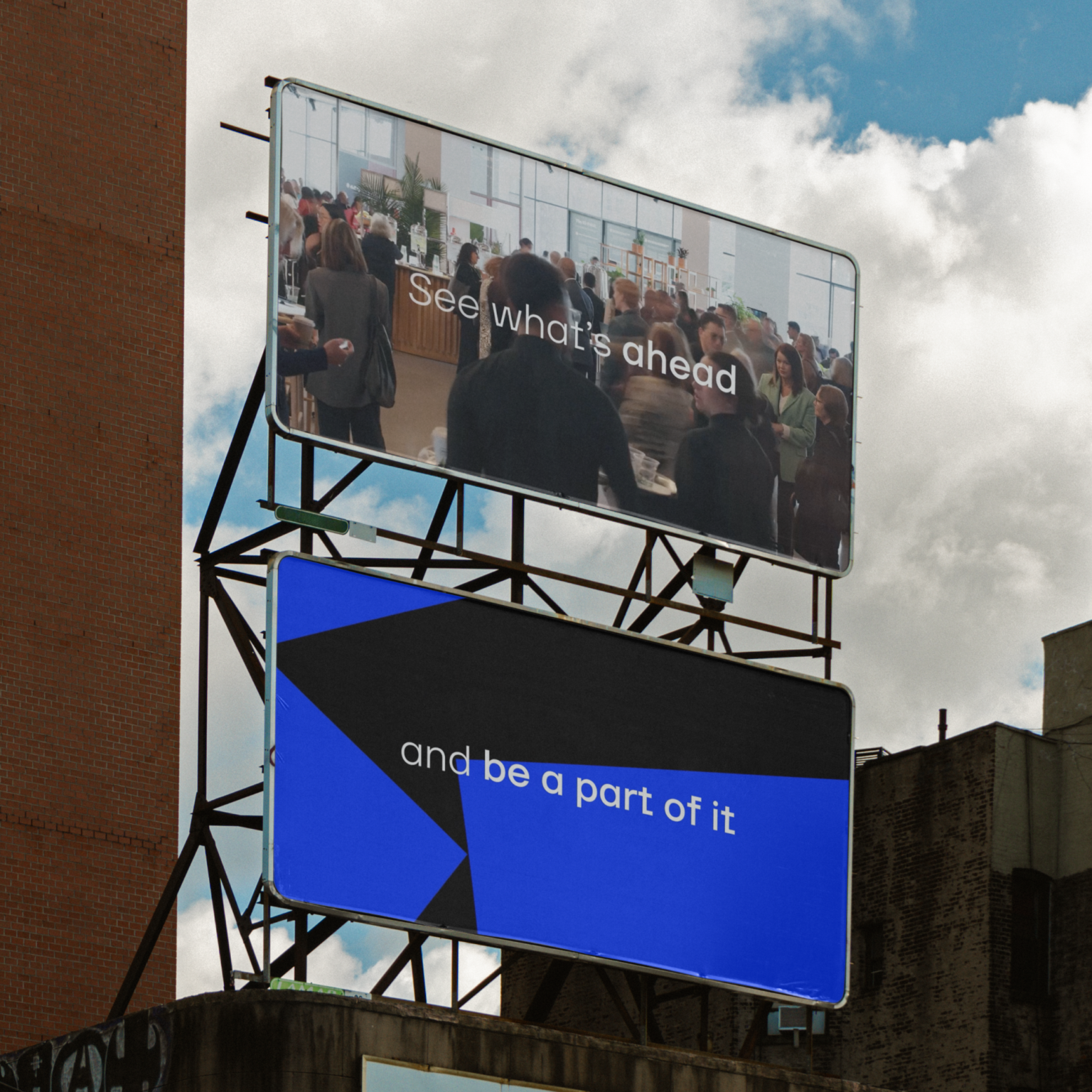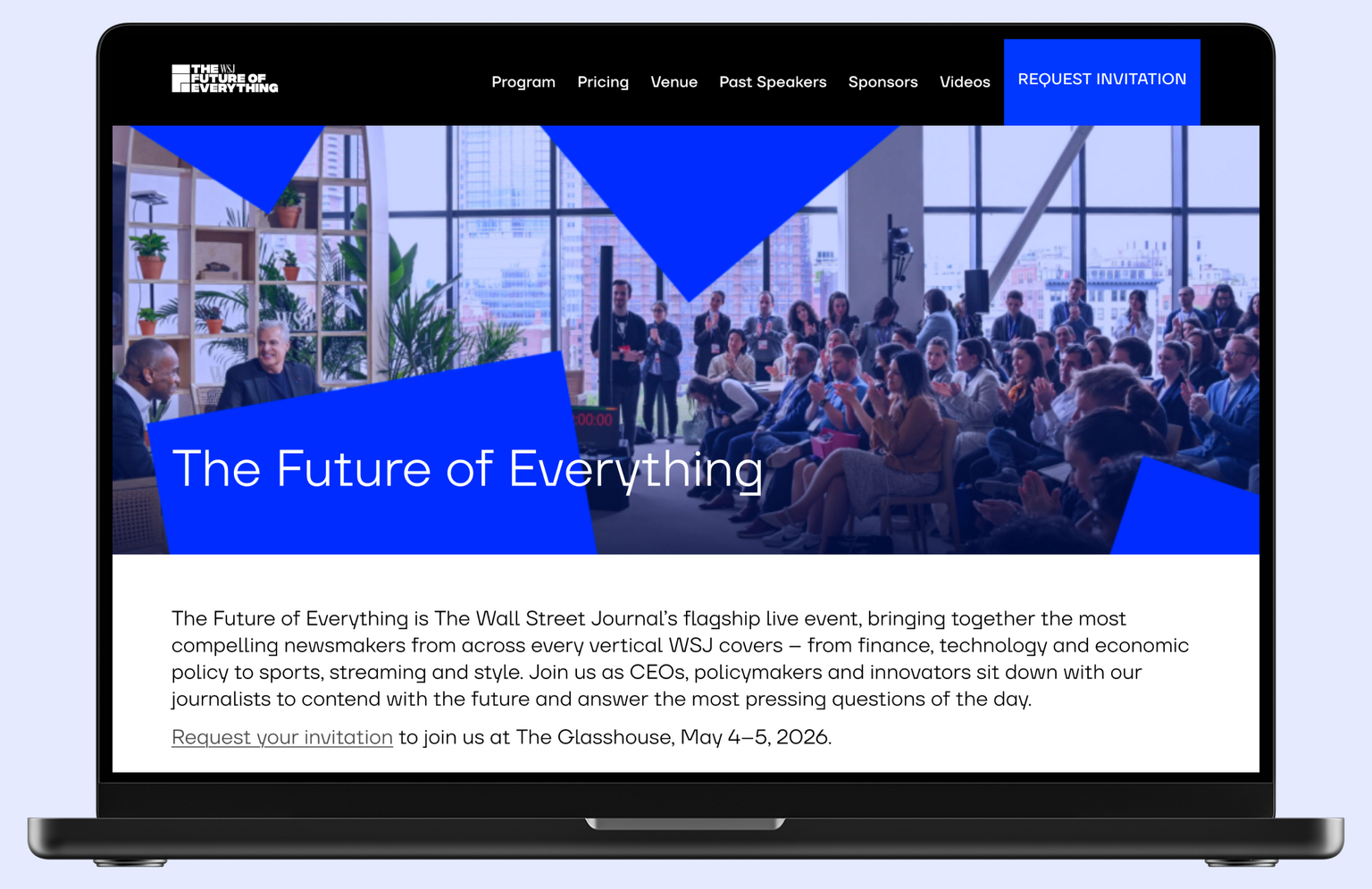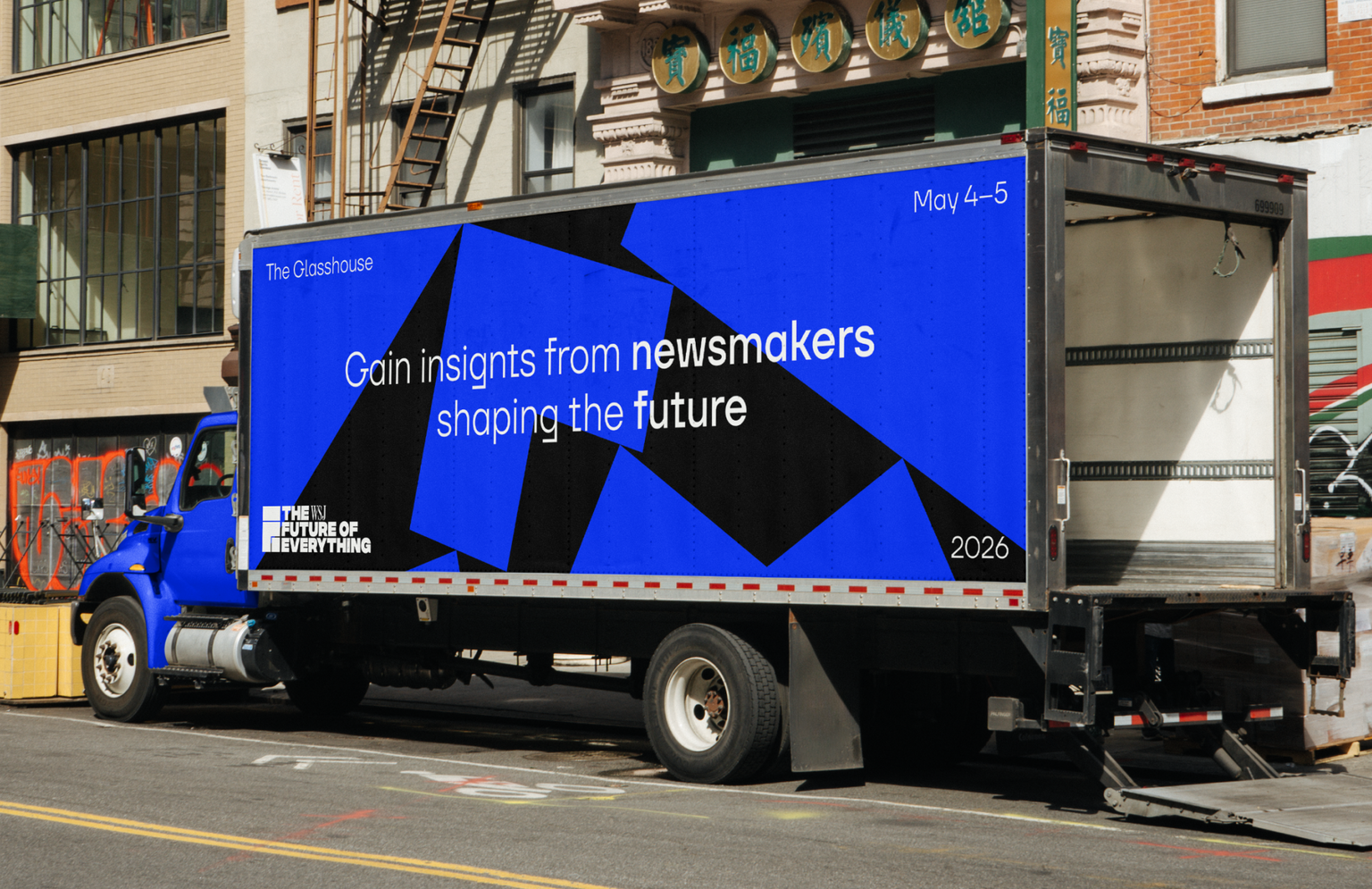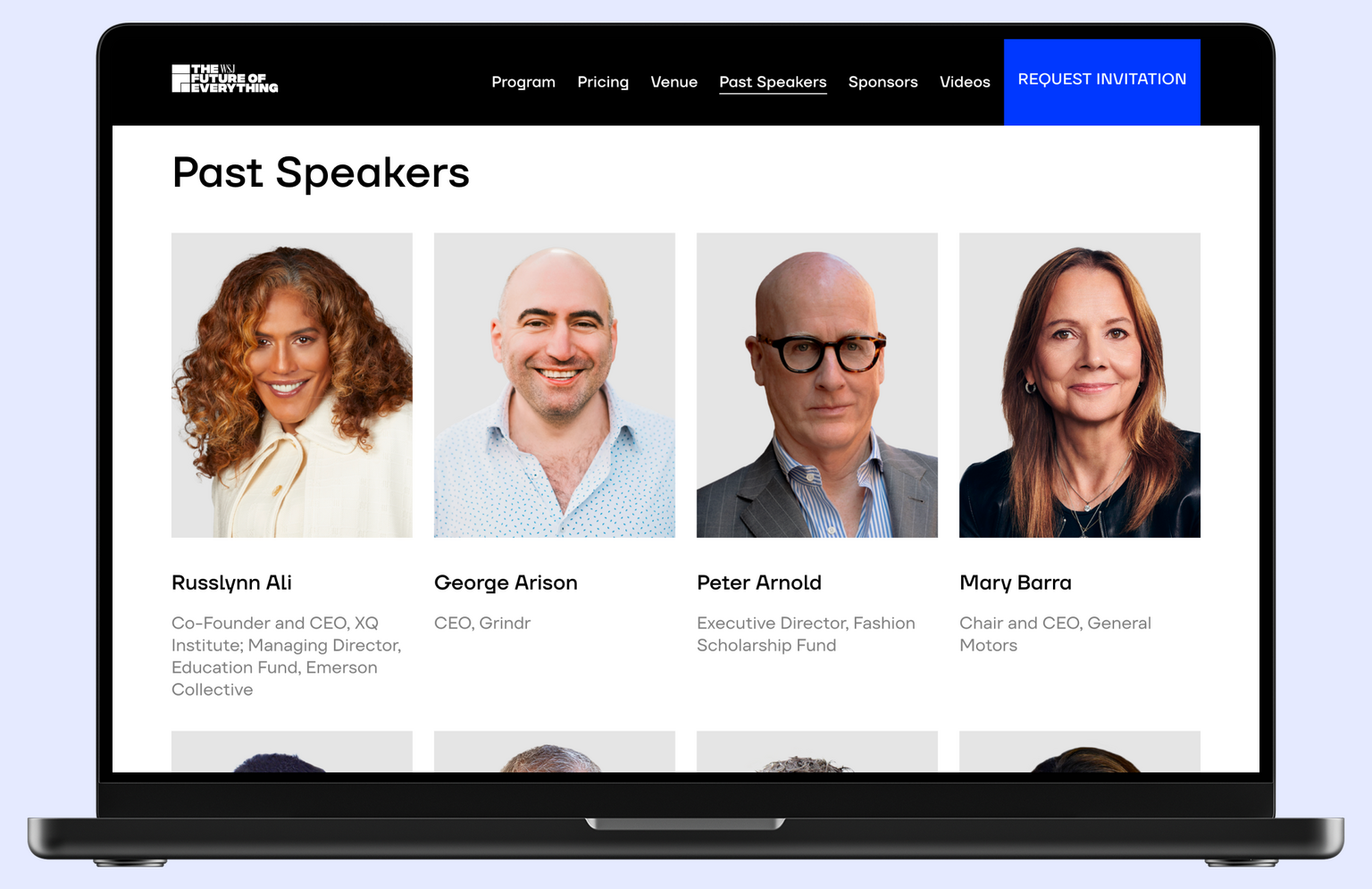
ТТ Фирс Нью (TT Firs Neue) — часть фирменного стиля The Future of Everything, фестиваля от The Wall Street Journal. Лаконичный шрифт передаёт деловой тон события и добавляет его стилю современное звучание и ясность.
The Future of Everything — это флагманское мероприятие, организованное The Wall Street Journal (WSJ), где журналисты WSJ вместе с лидерами в сфере бизнеса, технологий, политики и другими новаторами обсуждают ключевые тренды и самые важные вопросы, определяющие ближайшее будущее.